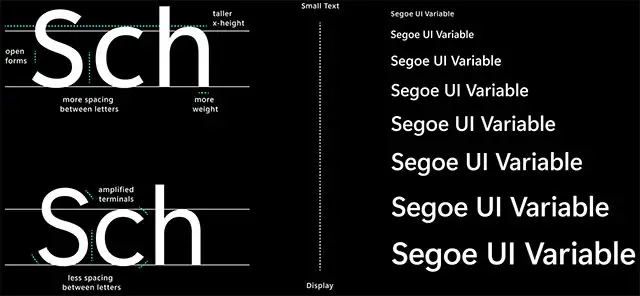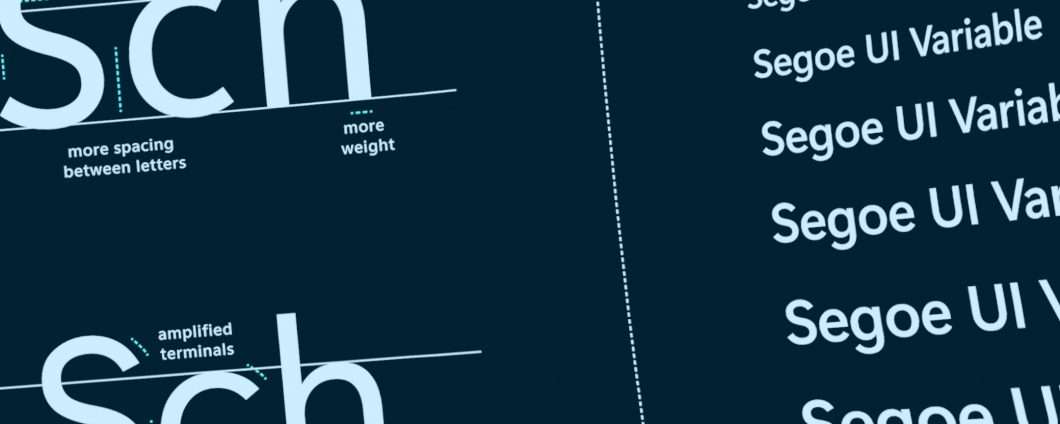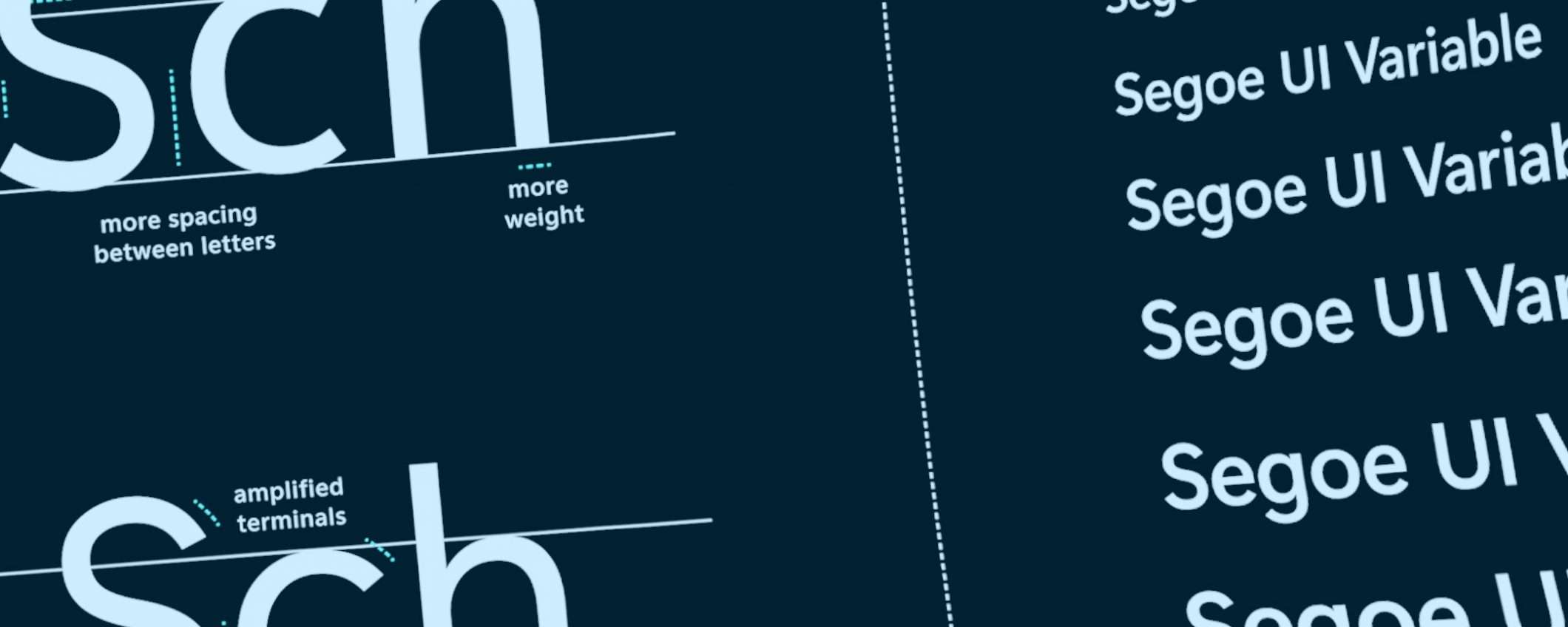
Gli utenti impegnati al fianco del gruppo di Redmond per il test delle versioni di anteprima di Windows 10 hanno ora modo di osservare Segoe UI Variable sui lori monitor. Il nuovo font è stato introdotto oggi con il rilascio della Build 21376, distribuita attraverso il Dev Channel. Ecco quanto si legge sulle pagine del blog ufficiale.
Storicamente, i font per i testi piccoli sono stati progettati in modo diverso da quelli per i testi grandi. Segoe UI è stato ideato in origine per funzionare a 9 pt, il che lo rende un ottimo carattere per quella dimensione, ma presenta limiti a dimensioni più grandi e la leggibilità è compromessa a dimensioni inferiori. Segoe UI Variable risolve il problema utilizzando una nuova versione di Segoe che fa leva su una tecnologia offrendo dinamicamente una leggibilità elevata a piccole dimensioni e uno stile impeccabile a dimensioni elevate.
Windows 10 cambia font: ecco Segoe UI Variable
Segoe UI Variable è studiato in modo da adattarsi al meglio a schermi di tutte le dimensioni, requisito fondamentale per una piattaforma come W10 che mira a essere presente su ogni tipologia di prodotto (ha già raggiunto 1,3 miliardi di dispositivi nel mondo). Un restyling del classico Segoe UI, a sua volta successore di Tahoma e con alle spalle ormai quasi due decenni di integrazione nei prodotti Microsoft.
Come scritto, l’obiettivo è anche quello di migliorare la leggibilità, soprattutto quando gli spazi si fanno stretti, come nel caso dei pannelli integrati sui form factor più compatti e portatili. Come sempre accade il rollout sarà progressivo e graduale, partendo dalle build di anteprima come quella oggetto dell’annuncio di oggi, per arrivare poi a interessare ogni componente del sistema operativo e per tutti.